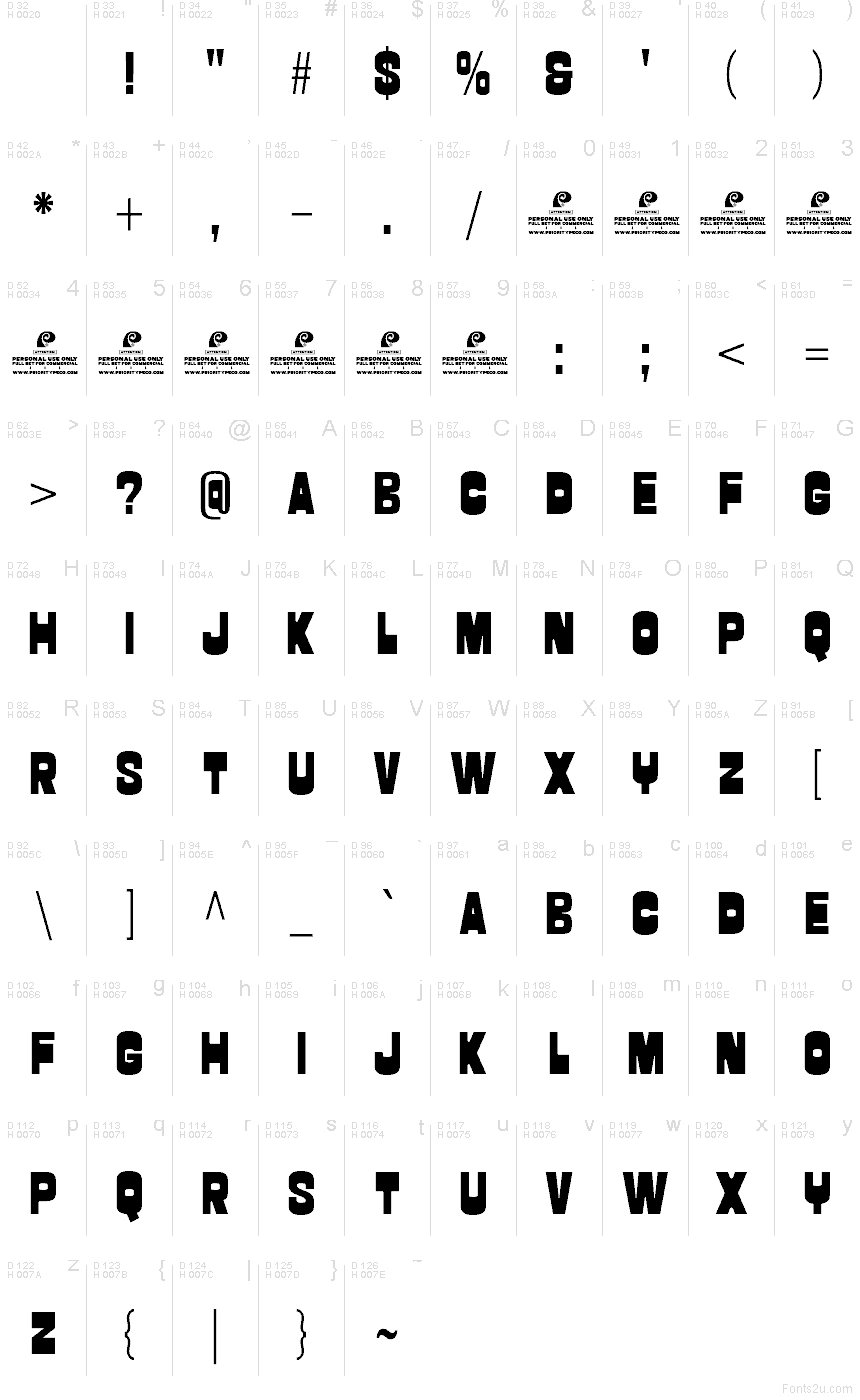
PC Merchis SemiCondensed od Prioritype Co. to darmowy font display w stylu groovy o przeskalowanych, ściśle ułożonych formach i surowej, industrialnej sylwetce. Niewielkie zaokrąglone otwory przecinają gęste litery.
Wyraziste geometryczne ilustracje stanowią doskonałe dopełnienie, nawiązując do szerokich łuków i kanciastych łączeń liter. Plakaty i grafiki muzyczne zyskują dzięki zwartej masie mocny, retrofuturystyczny głos. Merchandising oraz branding w branży rozrywkowej czerpią tę samą korzyść: liternictwo czyta się niemal jak indywidualny znak logo.